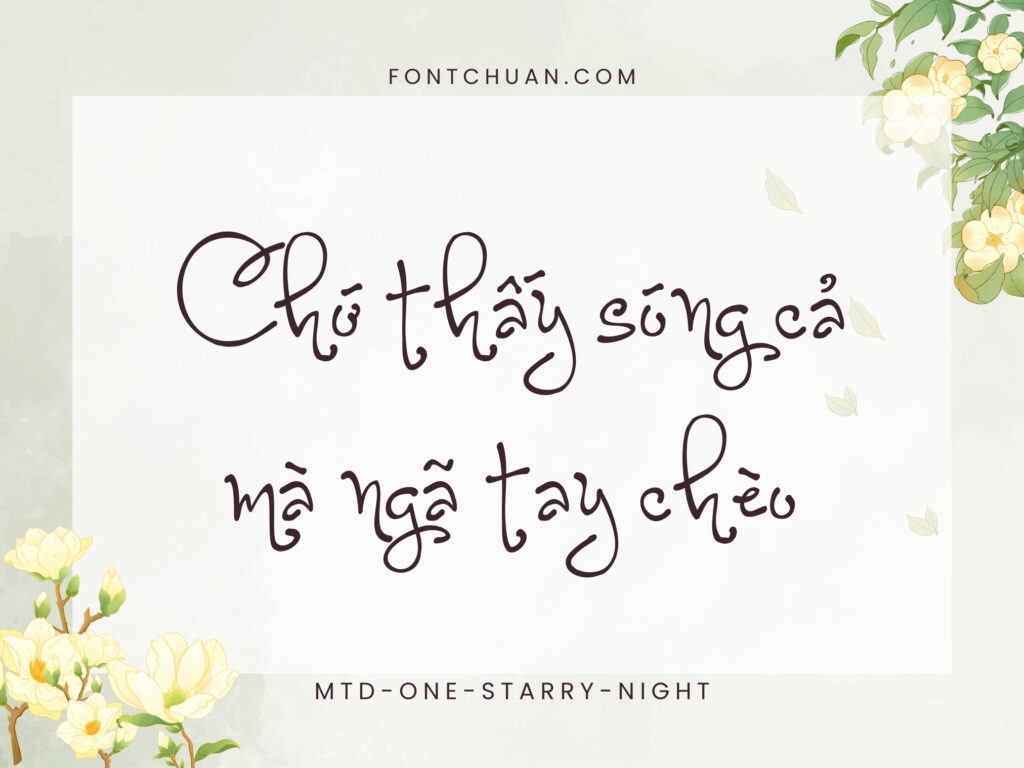
Font MTD One Starry Night Việt Hóa
Tác giả Font: Brittney Murphy
Font MTD One Starry Night là một phông chữ trang trí với các đường nét uốn lượn độc đáo, được thiết kế bởi Brittney Murphy và phát hành trên DaFont. Font đã được Việt hóa bởi Mộc Hạ, hỗ trợ tiếng Việt và hơn 90 ngôn ngữ khác, giúp mở rộng khả năng ứng dụng trong các thiết kế đa ngôn ngữ. Đây là một trong những phông chữ được cộng đồng thiết kế đánh giá cao và ứng dụng trong nhiều dự án sáng tạo, đáp ứng nhu cầu đa dạng của người dùng.
MTD One Starry Night nổi bật với phong cách vui nhộn và sáng tạo, mang đến cảm giác thân thiện và gần gũi. Font rất phù hợp cho các thiết kế tiêu đề, bao bì sản phẩm, thiệp mời và các ấn phẩm đòi hỏi sự độc đáo và nghệ thuật. Các ngành nghề phù hợp bao gồm quảng cáo, giáo dục, công nghệ, thiệp cưới và ảnh cưới. Font này cũng lý tưởng cho các sự kiện như Tết, Giáng sinh, Valentine và các lễ hội khác.